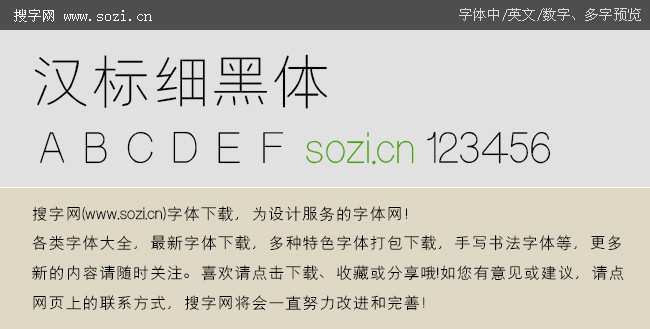
漢標(biāo)細(xì)黑體
搜字網(wǎng)給大家提供一款漢標(biāo)細(xì)黑體中文字體下載,漢標(biāo)細(xì)黑體字體字形正方,筆形簡練,簡約美觀。適用于正文排版、包裝設(shè)計、海報設(shè)計等應(yīng)用。(本字體為個人非商用版,如需要商用請聯(lián)系官方購買版權(quán))